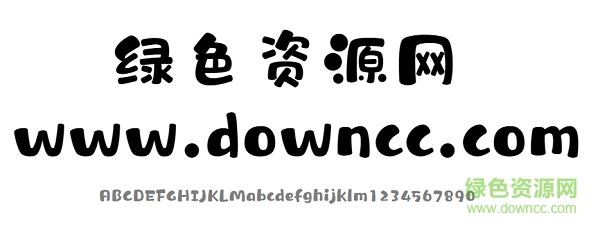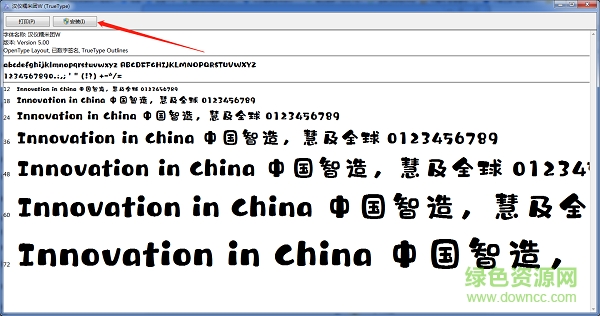
漢儀糯米團(tuán)w字體安裝包是綠色資源網(wǎng)小編為大家?guī)淼目蓯勖让鹊淖煮w,以糯米團(tuán)子為主要的靈感,將整個(gè)字體變的又矮又粗,看起來真實(shí)又萌又可愛哦,用戶可以使用字體編撰文章,打造出不同的排版特色哦,需要的用戶就來綠色資源網(wǎng)下載吧!
漢儀糯米團(tuán)簡(jiǎn)是一款適用性非常廣泛的個(gè)性風(fēng)格字體,該字體線條粗壯有力,連筆張弛有度,結(jié)體清麗優(yōu)美,其整體效果出色,能夠應(yīng)用于各種信息展示、網(wǎng)頁(yè)設(shè)計(jì)、篆刻制模、視覺設(shè)計(jì)、字帖等一切合法應(yīng)用場(chǎng)景,藝術(shù)與文字的結(jié)合,匯聚出更加美妙的效果!